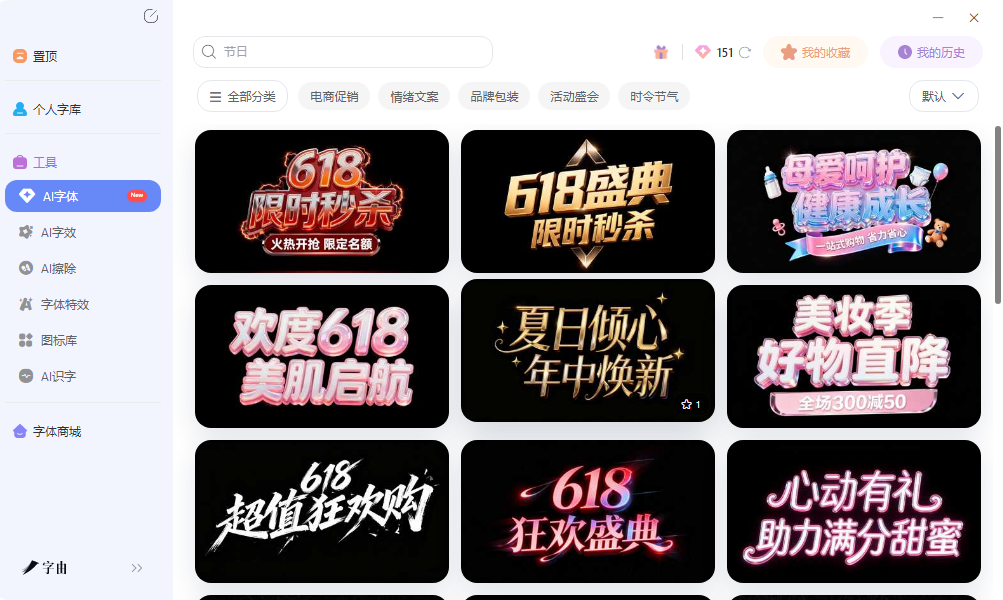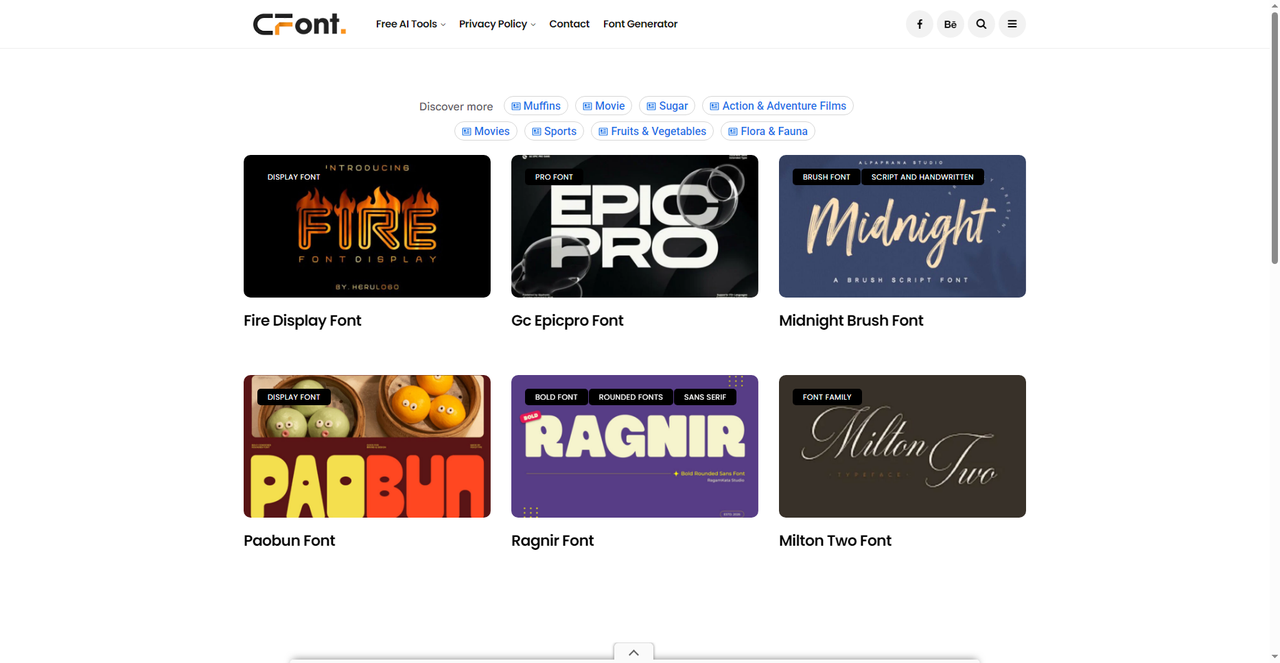
设计圈子里有个共识:同样的排版,换一款有性格的字体,效果能差出老远。创意免费字体下载渠道找对了,海报标题、品牌Logo、包装上的文字就能从"普通"变成"有辨识度"。这篇文章整理的五个平台,从风格强烈的展示字体到AI生成的创意文字效果都有,帮你把项目的视觉气质往上提一档。
字由提供两个途径来获取创意文字资源。第一个途径是字体库里的创意分类,收录了不少风格鲜明的中文字体,卡通、手写、艺术变形等类型都有,勾选免费商用标签后可以直接用于商业项目。预览框支持输入自己的文案实时查看效果,看到合适的点击激活就能在设计软件里调用。
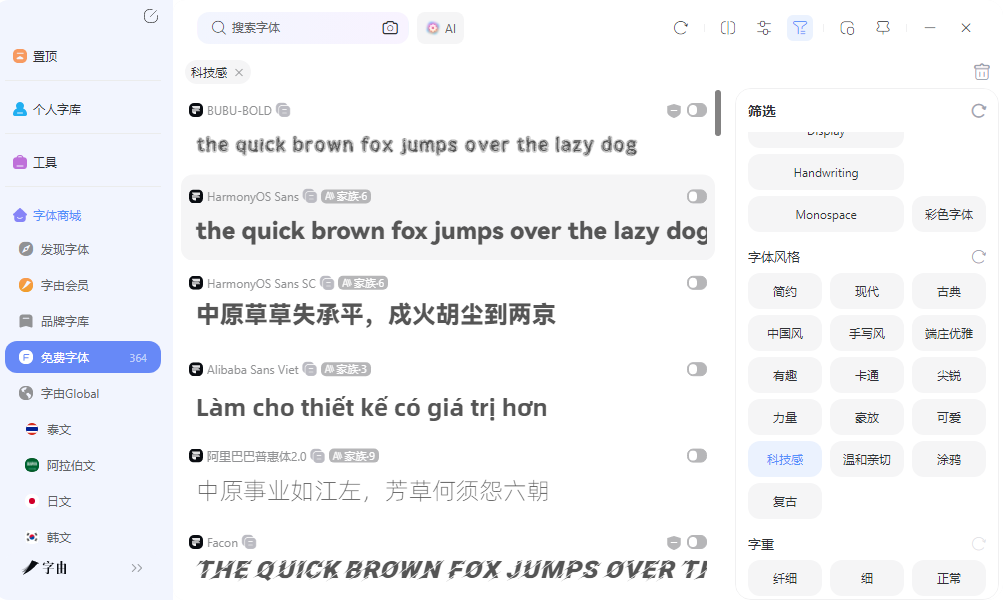
第二个途径是AI字体功能,这个更适合想要"创意文字效果"而不是"创意字体文件"的场景。选择模板、输入文案、生成图片,三步拿到成品。模板库里有不少视觉冲击力强的风格,水墨效果、鎏金质感、霓虹发光、火焰特效、立体金属等都覆盖到了。这些效果是常规字体文件本身不具备的——在其他创意免费字体下载网站找到的创意字体,安装后在PS里打字还是平面的;而AI字体直接产出一张带特效的图片,层次感完全不同。
两种方式的区别在于,字体库提供的是字形本身,设计师自己决定排版和用法;AI字体提供的是成品视觉,适合时间紧、需要快速出效果的场景。比如做一张活动海报,标题需要强烈视觉冲击力,用AI字体直接生成特效文字比从字体库里挑一款再自己调效果要快得多。搭配起来用比较灵活,平时积累创意字体,紧急时候用AI字体救场。免费用户每日有算力额度,登录赠送的点数足够应付日常轻量使用。
2、CFont
CFont的页面一眼看去就很有创意气质。首页展示的几款字体风格跨度很大:Fire Display Font是火焰主题的展示字体,笔画带有燃烧效果;Gc Epicpro Font带有金属光泽和科技感;Midnight Brush Font是手写风格的英文笔刷体;Paobun Font的字母造型圆润有趣,适合做食物或儿童类项目;Ragnir Font是粗圆的无衬线体,现代感强;Milton Two Font则是优雅的衬线体。
3、Creative Market Free Fonts
Creative Market是一个大型创意资源交易平台,Fonts板块下面有一个Free Fonts专区,目前收录了超过12万件免费字体数字资产。这个体量的优势很明显,你想要的风格几乎都能找到,从复古手写体到现代无衬线体,从装饰性强的展示字体到简洁的正文字体,覆盖面很广。
页面左侧有Categories分类导航,All、Photos、Graphics、Fonts、Mockups等维度可以帮助快速定位。首页展示的Glitz、Quandary、Chicago Downton等字体风格各异,有的适合做复古海报,有的适合做品牌标识。还可以按Staff Picks和Featured Shops筛选,这些经过平台推荐的字体通常品质更高一些。
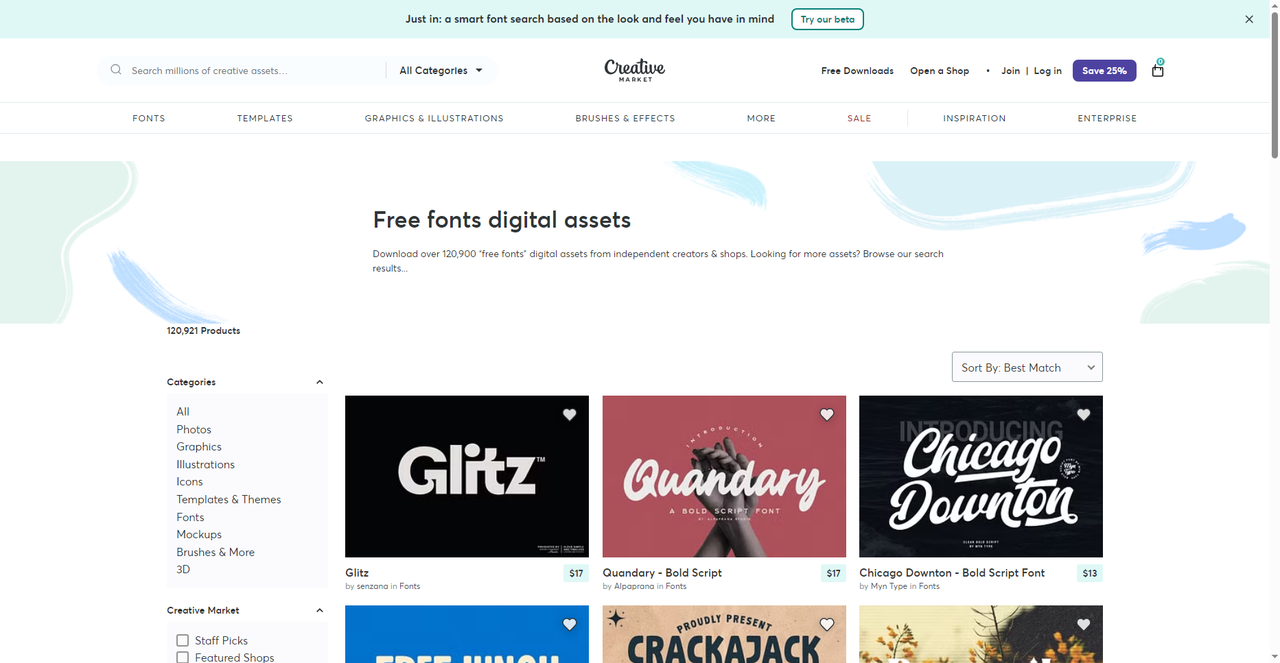
4、Fontsum
Fontsum的定位是"Creative Free Fonts for Every Design Project",主打精选路线。页面顶部的风格标签覆盖了Serif、Sans Serif、Script、Display、Blackletter、Handwritten、Monospace、Dingbat等类型,点击即可筛选,不需要在海量结果里翻找。
展示的字体风格都比较有个性,Green Fuz带有街头涂鸦感和骷髅元素,Graffiti Treat是明显的喷涂效果,Got No Heart是泡泡字体风格,Goldsaber有科幻机甲感,Golden Girdle则是几何变形风格。每款字体都明确标注了"Commercial Free",商用授权清楚,下载后可以直接进项目,不需要再花时间确认授权。
Fontsum的"Recently Added"和"Most Popular"两个板块更新比较及时,经常能看到新上架的创意字体。对于想快速找到一批风格独特、授权放心的创意免费字体下载资源的人来说,Fontsum的精选机制比较省心,不用自己从海量结果里筛选。
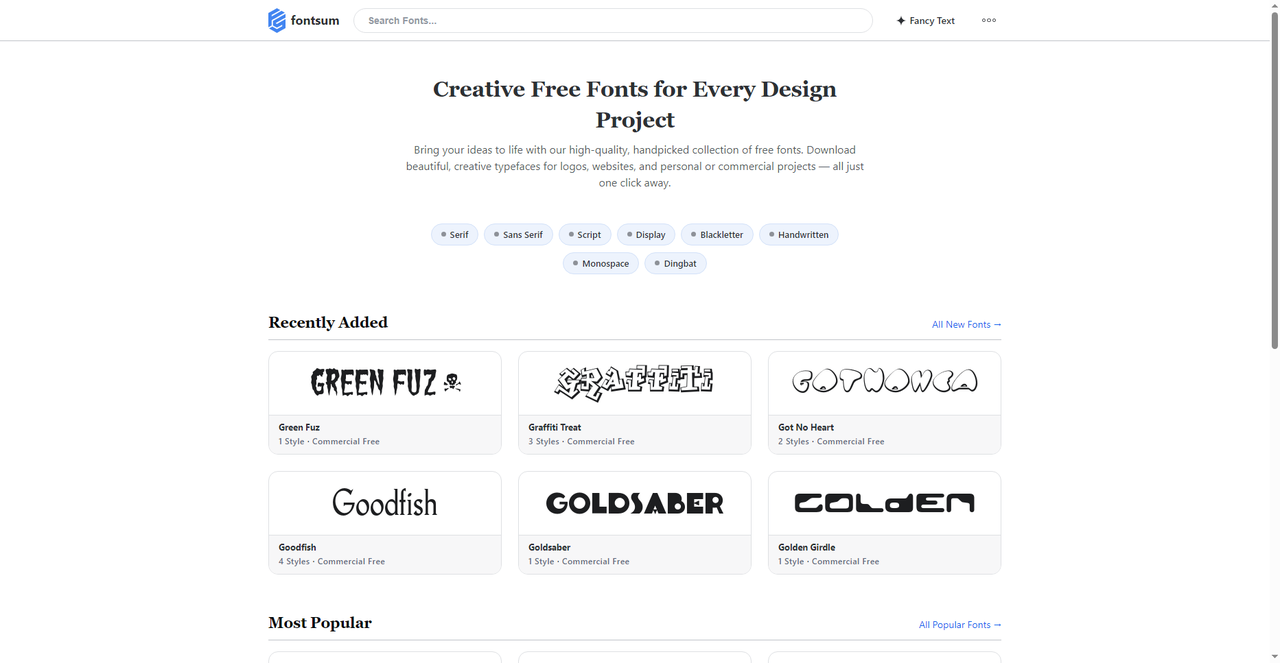
5、Fontesk
Fontesk是一个按基础字形分类的免费字体平台,导航包括All Fonts、Sans Serif、Serif、Slab Serif、Script、Display、Handwritten。筛选区域提供了Free for Commercial Use、Free for Personal Use、OFL等授权选项。
平台上展示的创意字体不少,Brigend Font是手写风格,Eastern Rhodopes带有异域装饰感,Nekta是简洁的现代无衬线体,Native Letter和Philyou Display则是视觉冲击力的展示字体。分类加授权的交叉筛选让找字效率比较高,尤其适合有明确方向的设计师——知道想要什么大类,直接点进去看就行。Fontesk的更新频率不错,经常能看到新的创意字体加入,作为长期关注的创意免费字体下载渠道比较可靠。